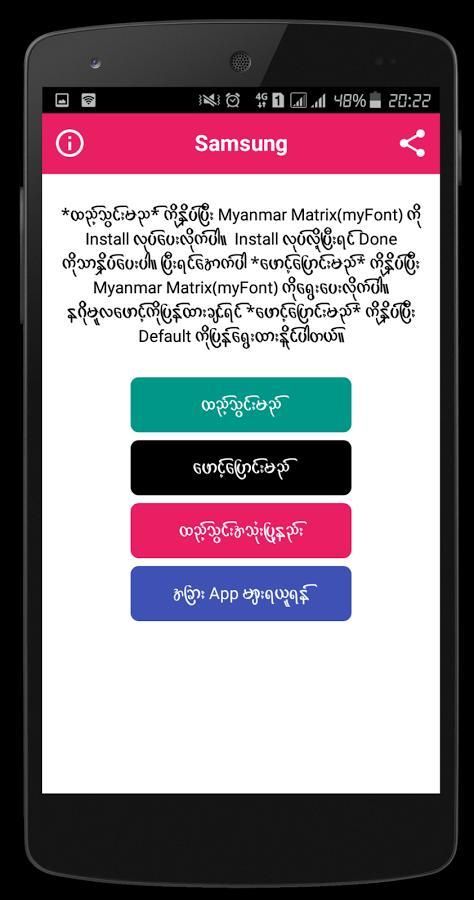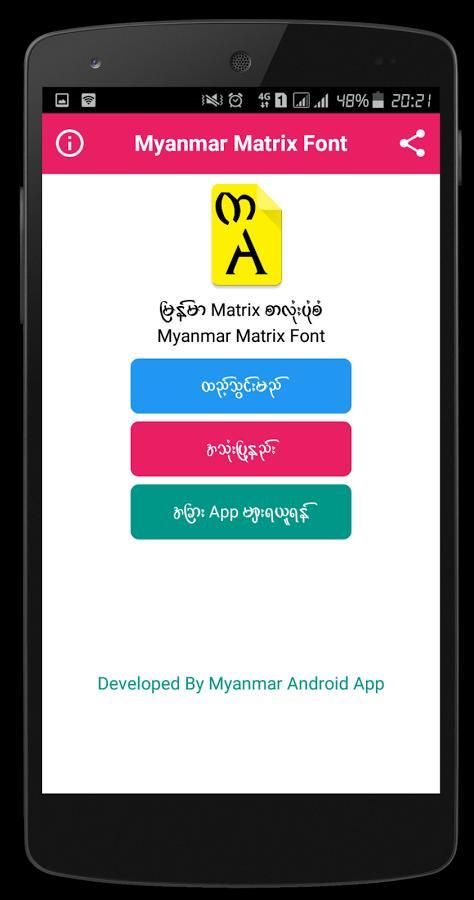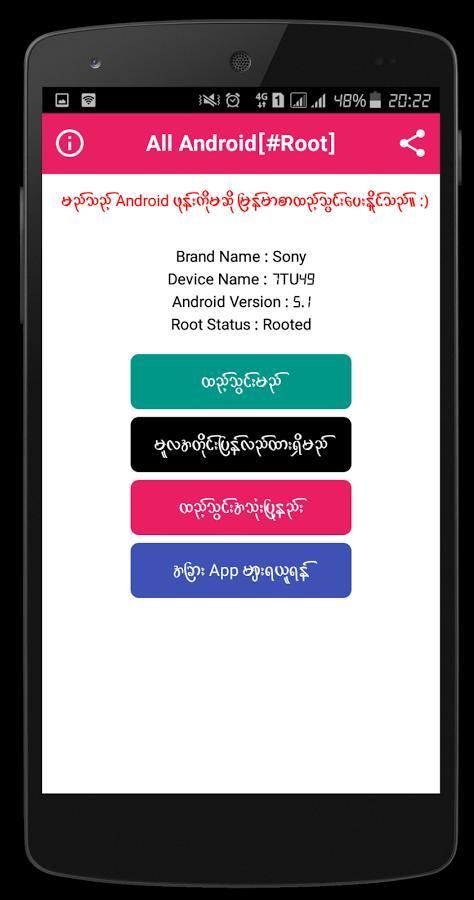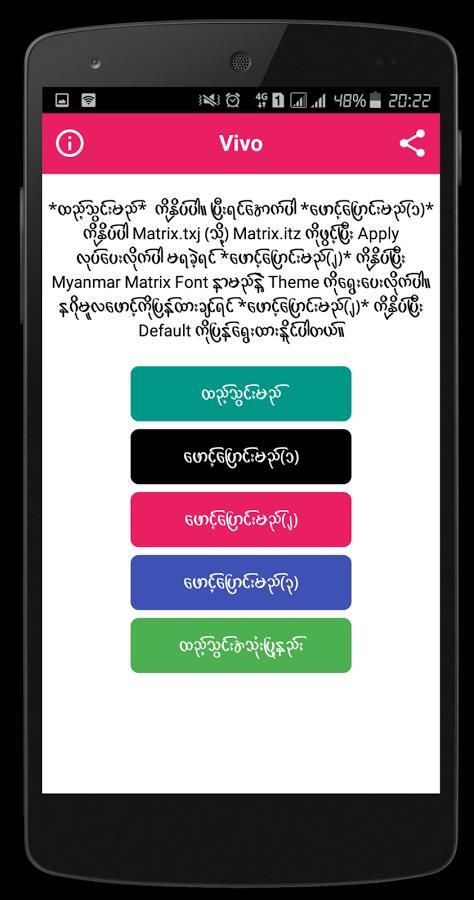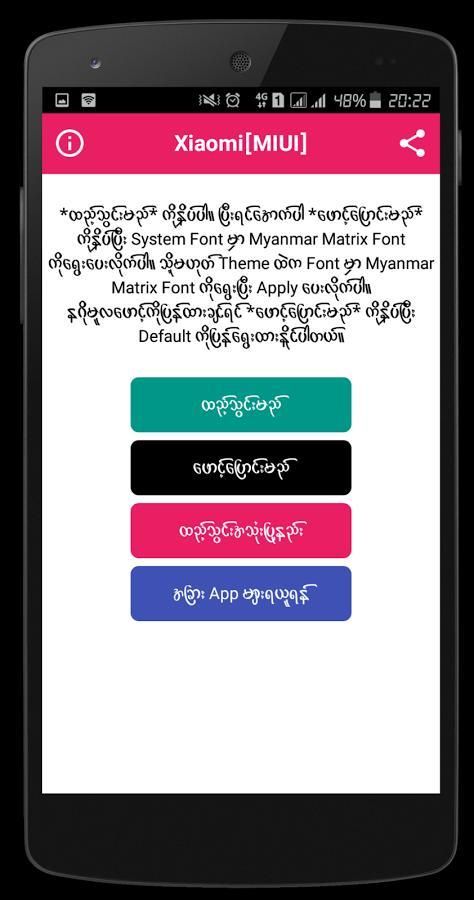
"Myanmar Matrix Font" Root မလိုထည့္သြင္း ျမန္မာစာလုံးအလွတစ္ခုျဖစ္ပါသည္။
ဖုန္းမွာျမန္မာစာလုံးအလွသုံးခ်င္သူမ်ားအတြက္
Myanmar Matrix ဆိုတဲ့စာလုံးအလန္းေလးတစ္ခုပါ။
အရမ္းလန္းပါတဲ့စာလုံးပုံစံေလးပါ။